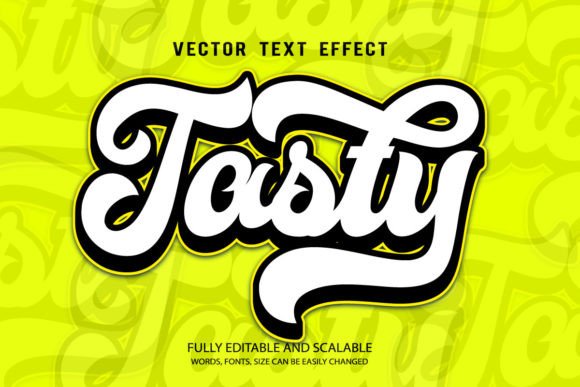
Tasty Modern Lettering Typography Font
Die richtigen Designelemente zu finden, kann eine Herausforderung sein, aber Tasty Modern Lettering Typography Font bietet eine außergewöhnliche Sammlung, die Ihre Arbeit sofort aufwertet.
Mit Präzision gefertigt, bietet Tasty Modern Lettering Typography Font saubere Vektoren, eine reibungslose Typografie und eine kommerzielle Lizenz für ein beruhigendes Gefühl.
Egal, ob Sie POD-Produkte (Print on Demand), Hochzeitseinladungen oder Social-Media-Grafiken erstellen, Tasty Modern Lettering Typography Font ist die ideale Wahl.